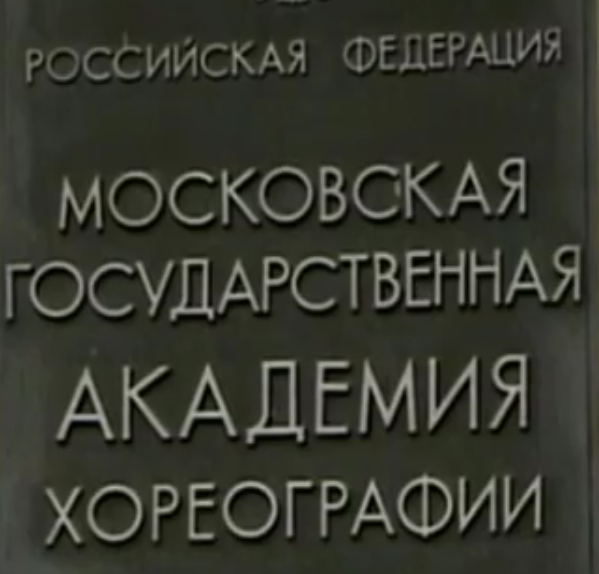
wie heisst dieser ugly type
für einen Freund suche ich nach diese "Schrift". Quelle Rumänien
und als Bonusfrage: warum die Russen den R und den N falsch rum verwenden?
(beim X ist optische Mittelachse zu niedrig). An diese Schrift kann ich mich auch schwach erinnern, also nicht.
Was ist denn an P und H falsch rum?
ich glaube, er meint: warum verwenden russen Я (scheinbar gespiegeltes lateinisches R) und И (scheinbar gespiegeltes lateinisches N)? in den wikipedia-artikeln, die ich mit den buchstaben verlinkt habe, ist zu lesen, dass sich die formen jeweils unabhängig von denen des lateinischen alphabets entwickelt haben und nicht von R oder N abgeleitet sind. dass sie bisweilen von schriftgestaltern, die schnell mal kyrillische buchstaben zu einer schriftart hinzufügen wollen, tatsächlich durch reine spiegelung von den lateinischen formen abgeleitet werden, ist wohl eine eher neue entwicklung.
Klar haben die sich unterschiedlich entwickelt, da ja (extrem vereinfacht) nicht das lateinische Alphabet Pate des kyrillischen war, sondern das griechische. Unser R ist ja etruskischen Ursprungs.
Und wie heisst die Schrift auf den Schild der Bolshoi Balletschule?
»Buchstabengießereieigenanfertigung«? :-?
Ansonsten finde ich die Realisierung des й interessant, das aussieht wie и́ (и mit Akut). War das irgendwann mal akzeptabel? Oder ist die linke Hälfte des Breve einfach nur irgendwann abgebrochen?
Es ist nicht auszuschließen, dass das ein Versehen bei der Fertigung war. Aber auch Typedesigner spielen ja gern mit der optischen Mitte und entsprechenden Erwartungen. Tiefergelegte Querstriche bei A/E/F findet man ja häufig. Aber auch solche scheinbar »verkehrt herum« gestalteten Buchstaben findet man immer wieder. Zum Beispiel das S der Original-Bleisatz-Weiß-Antiqua:
Liebe Typophile Kollegen! das mit den Smileys geht mir als geborenen Spaßmacher ganz knapp am dings vorbei. Ich benutze sie nur als Zugabe weil ich davon ausgehe das meine Leser  Bei mir geht (ganz ernst) auch verbal live grundsätzlich kaum etwas ohne Humor. Die Rumänische Schriftprobe su che ich immer noch. Scheint echt schwer zu sein.
Hallo Ralf. Danke für feedback. Der Text ist Teil des "Logramms" des Bukarester Univerlags, ca 10 Jahre alt.
Vielleicht hilft das?